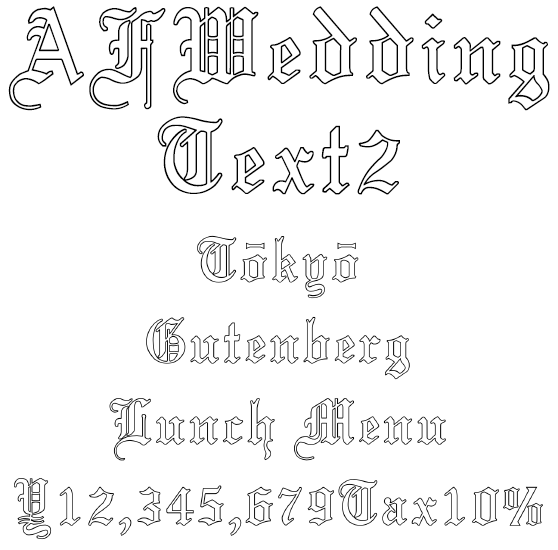
アメコミ古文書 欧文フォント AFWeddingText2Rev
AFWeddingText2Rev
ウエディングテキストは、ヨハネス・グーテンベルクの四十二行聖書にも似た書体、ブラックレターの中では比較的読みやすい欧文フォント。既存のAFSWeddingTextに記号と日本のローマ字表記で使われる訓令式やヘボン式の Ô や Ō を追加収録。さらに文字間とカーニングを調整後、袋文字化しました。洋食メニュー、アメコミでの古文書を模したProps、Tease、Key visual にご利用ください。